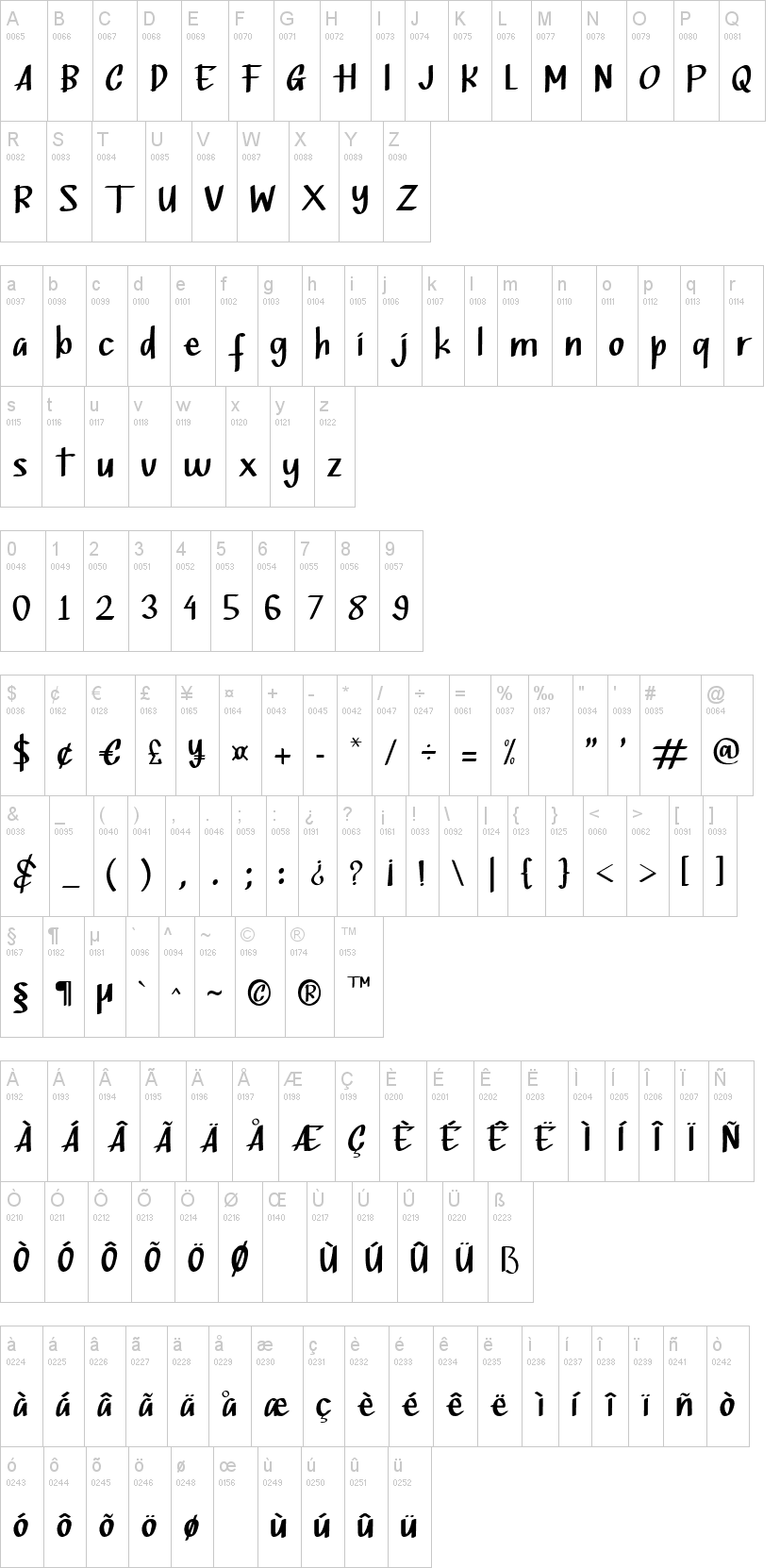
Bottsen Zatte 是一种荷兰风格的手写字体,具有非常独特的草书风格。它的笔画粗细变化很大,看起来非常自然而有机。这种字体的设计灵感来源于荷兰的啤酒品牌“Bottsen Bier”,因此其名称中的“Bottsen”代表啤酒,而“Zatte”是荷兰语中“醉汉”的意思。 Bottsen Zatte 字体具有很好的可读性和可用性,非常适合用于海报、标志、包装和其他各种设计项目中。该字体包括大写字母、小写字母、数字和常见的标点符号,可以在许多设计项目中轻松使用。它还具有多种不同的字重和风格,可根据需要进行选择。总之,Bottsen Zatte 字体是一种非常有趣和富有个性的字体,可以为设计项目增添独特的风格和特色。内容介绍
Bottsen Zatte是一款非常不错的手写艺术字体,具有很好的视觉感,适合于文化类的宣传设计、商业类品牌的广告和产品包装设计以及个性化文字排版等较多场景。